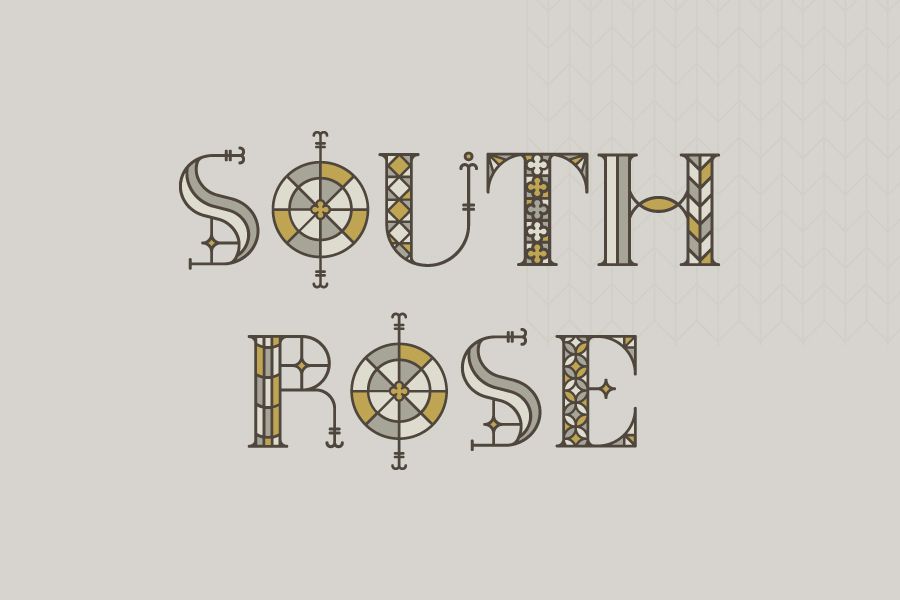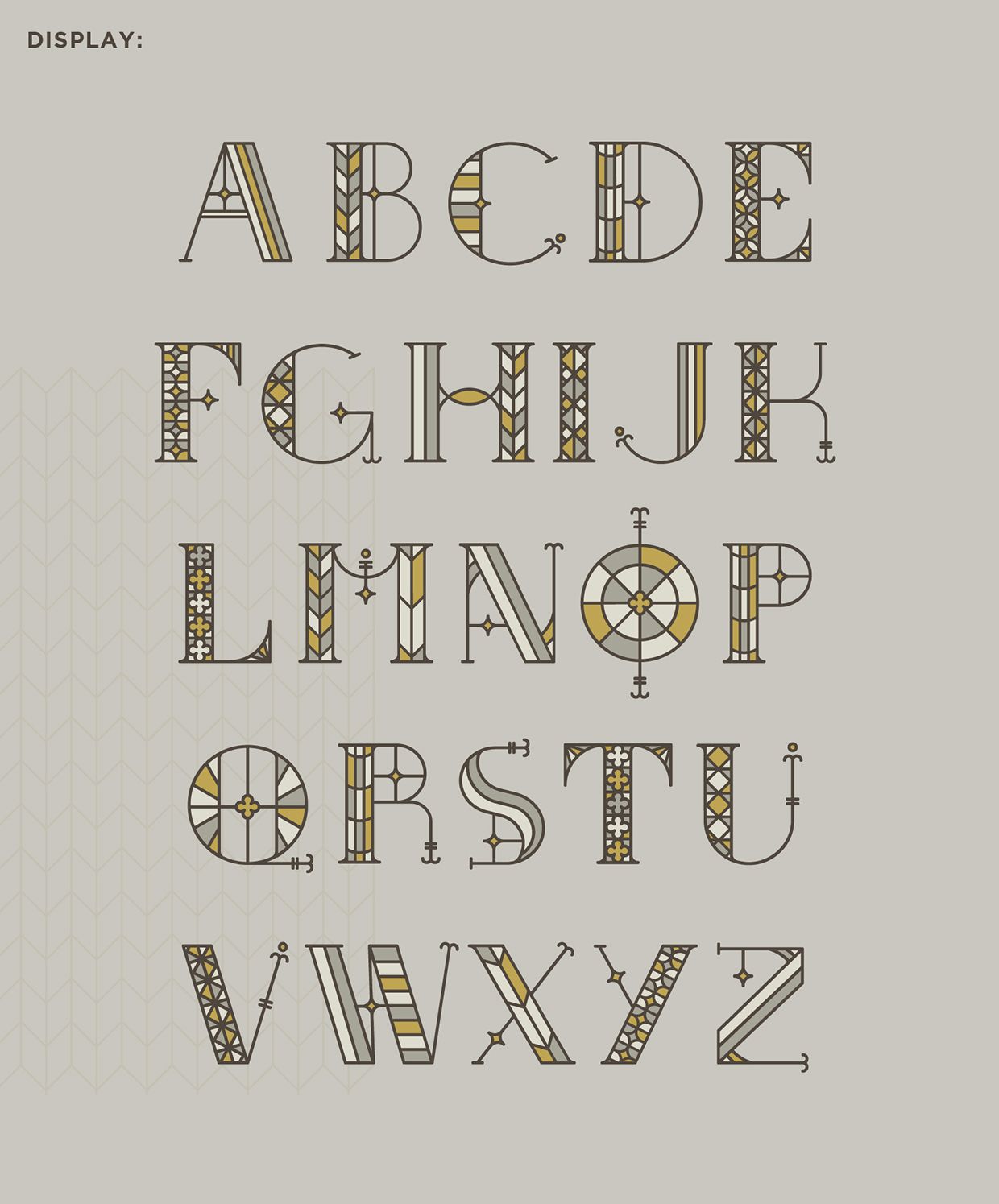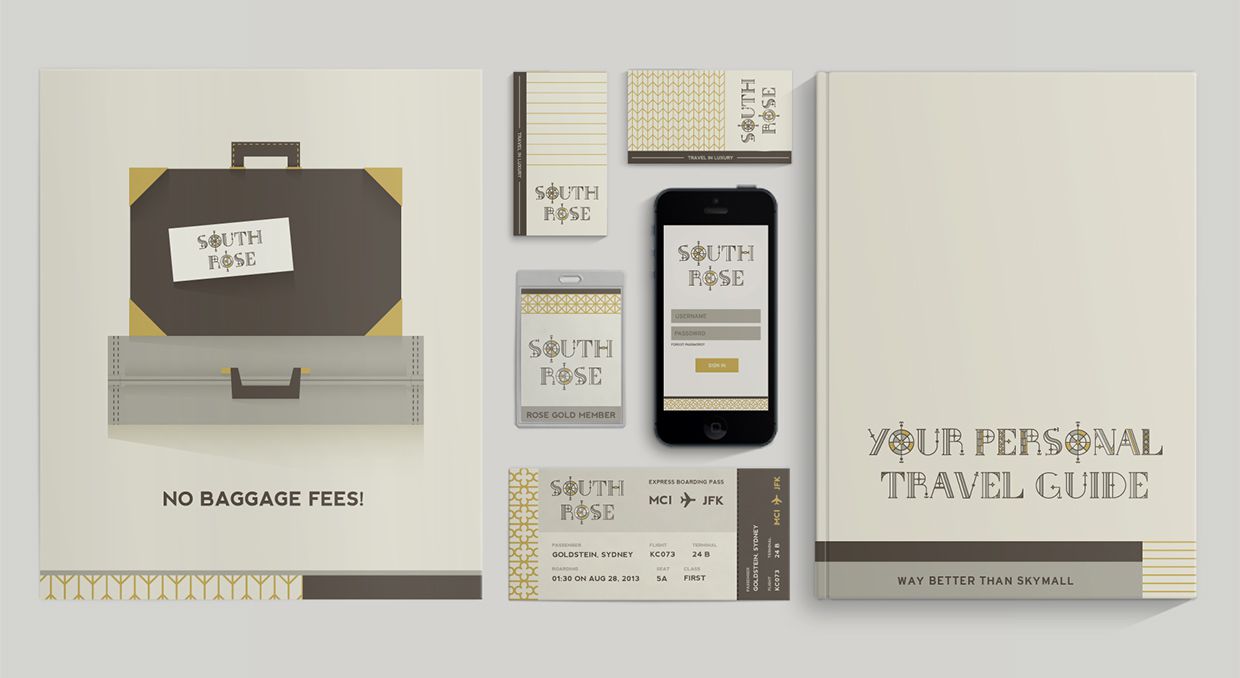
Basada en el rosetón del sur de la Catedral de Notre Dame. South Rose es un bonita fuente tipográfica llena de curvas y con sabor a viajes. Gracias a la ilustradora Norteamericana Sydney Goldstein, podemos disfrutar de esta estupenda fuente tipográfica totalmente gratis.